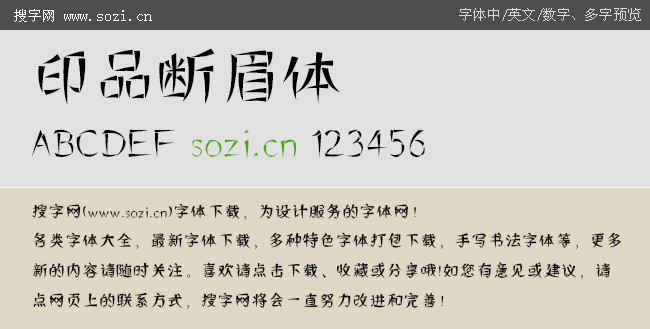
印品斷眉體
搜字網(wǎng)給大家提供一款印品斷眉體中文字體下載,印品斷眉體字體是一款設(shè)計(jì)靈感來(lái)源于中羽玉眉形狀的字體,風(fēng)格明快而極具個(gè)性,字體給人的印象纖秀靈動(dòng),看上去非常的獨(dú)特。適用于搭配標(biāo)志、廣告標(biāo)語(yǔ)、商業(yè)廣告等廣告設(shè)計(jì)。